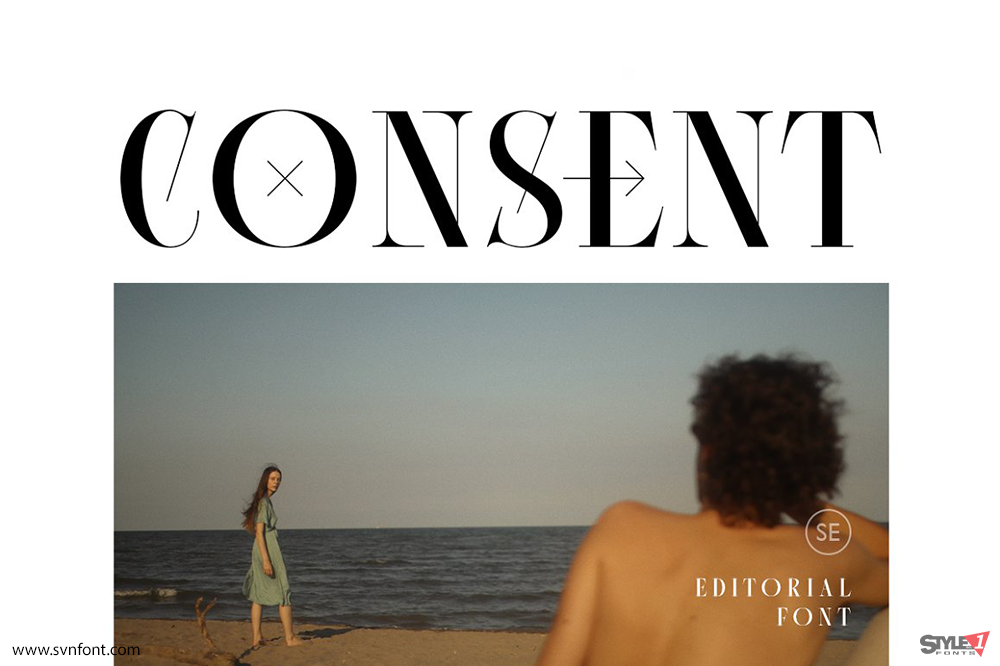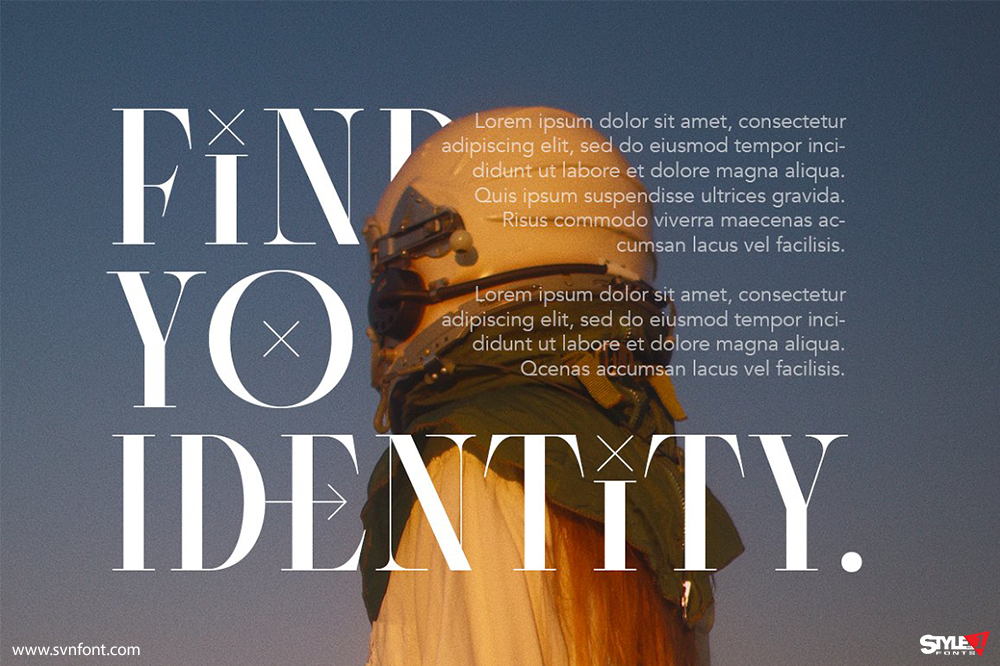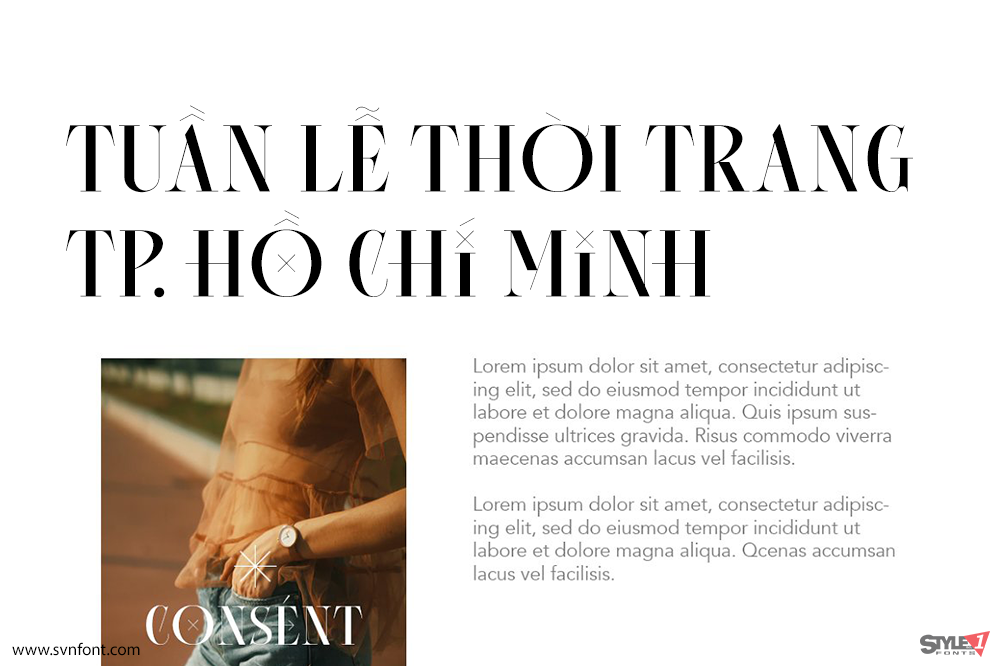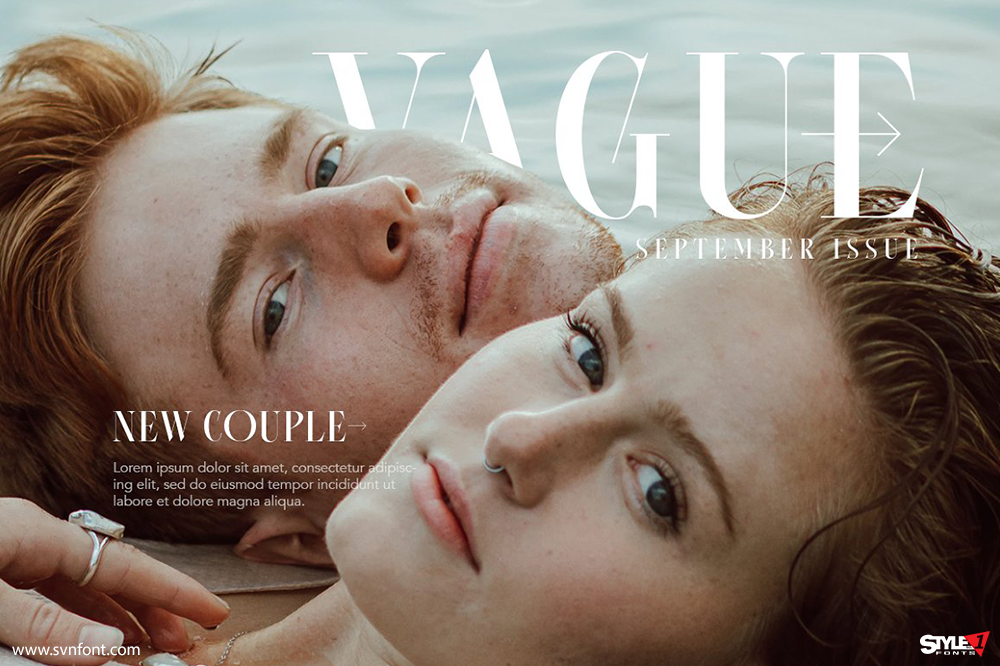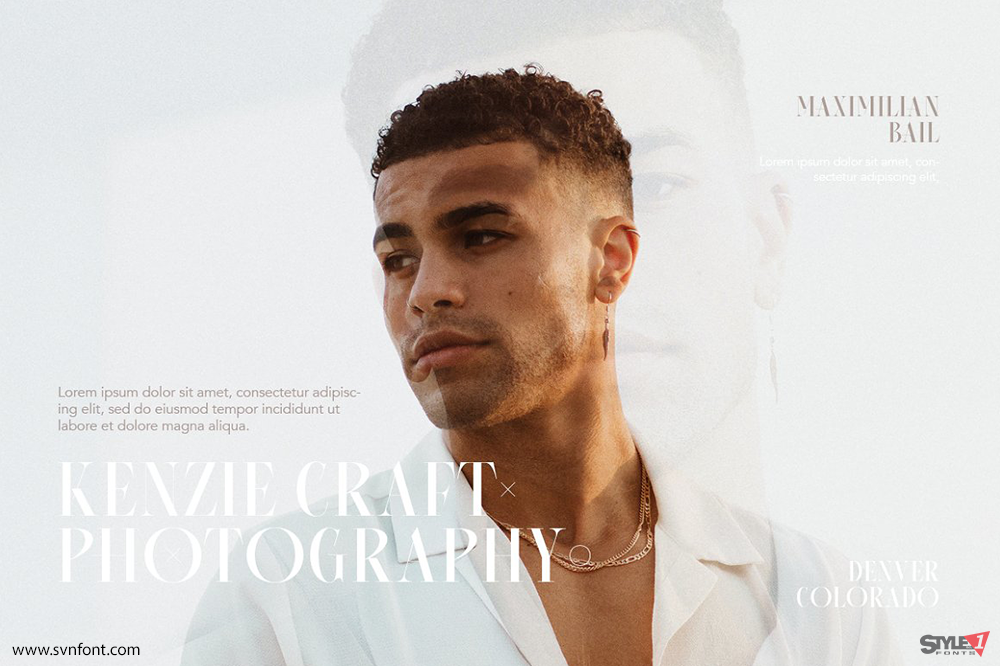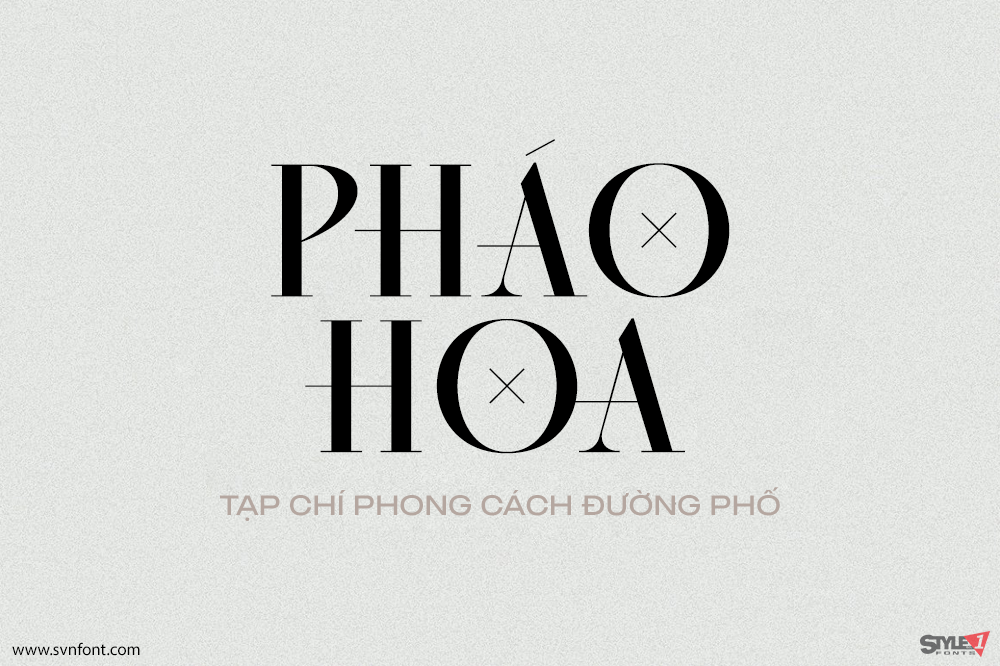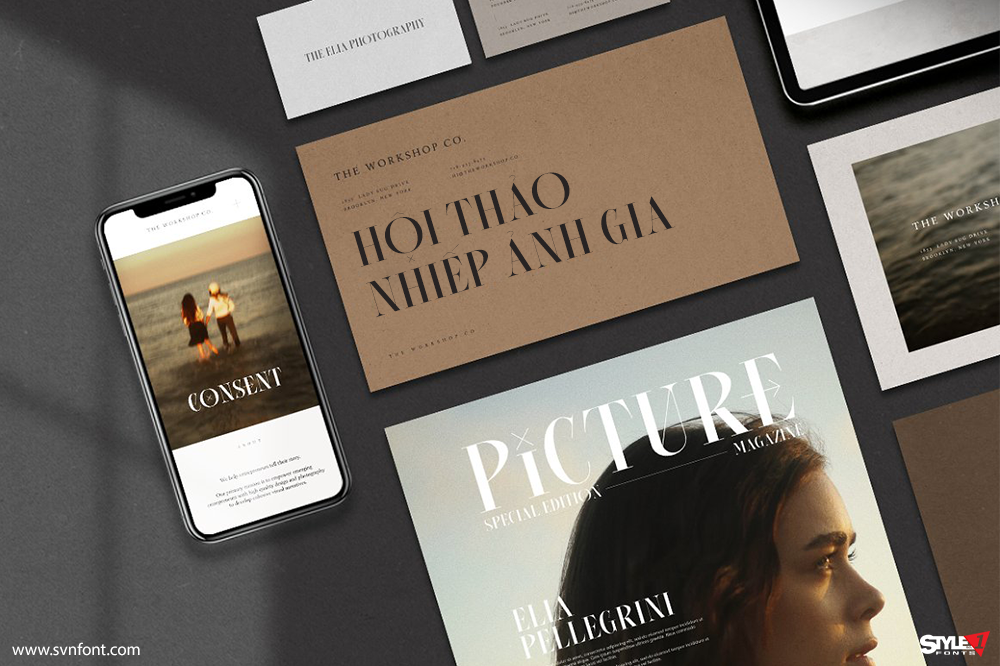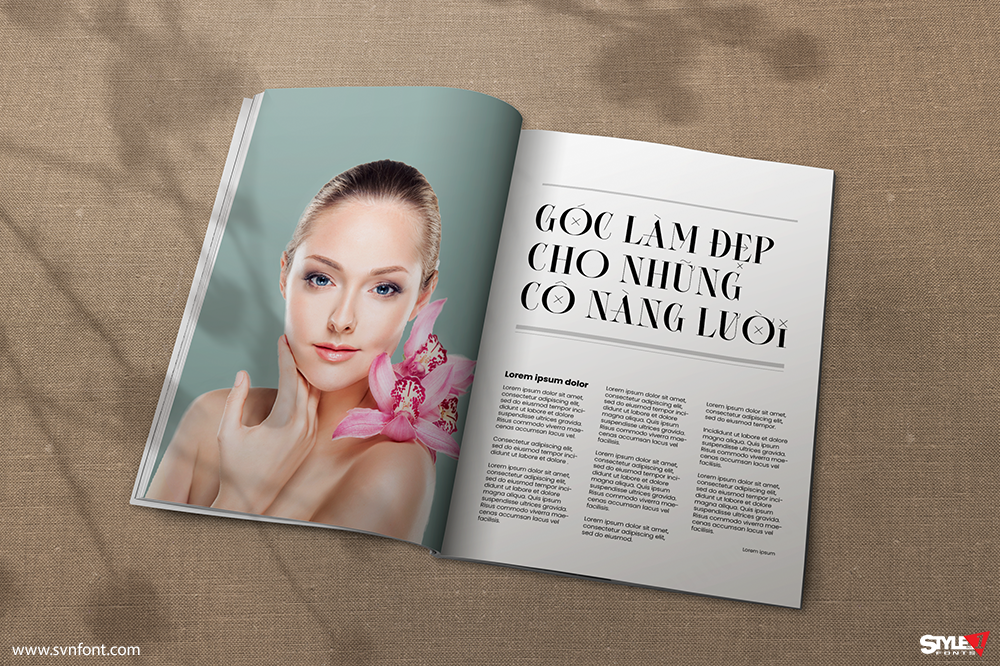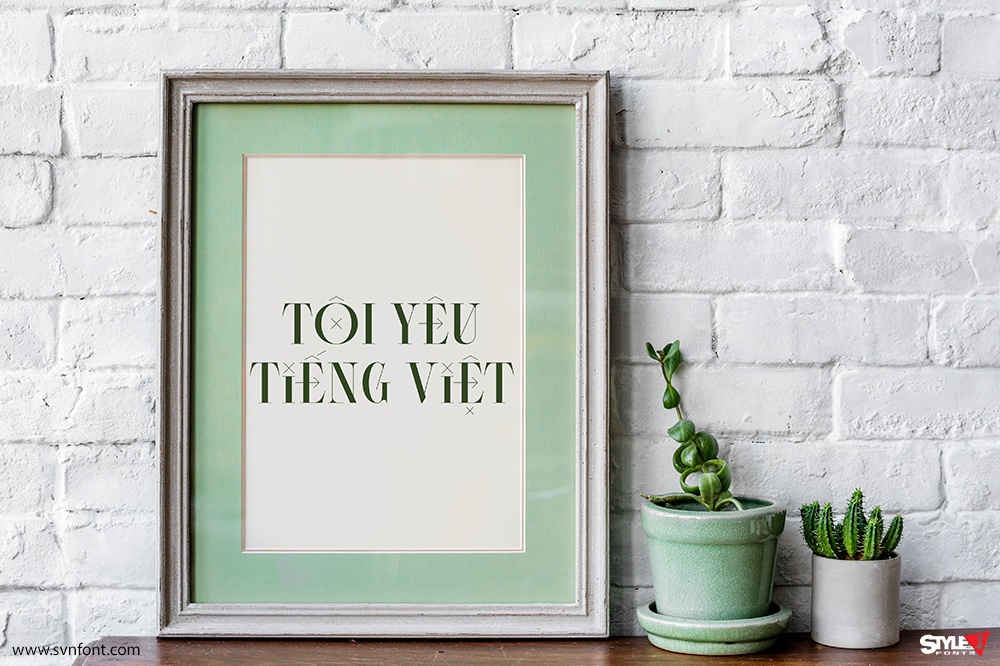
Consent là một font chữ serif mang phong cách biên tập với chữ thường độc đáo. Nhờ các tính năng đặc biệt, Consent sẽ giúp dự án của bạn trở nên nổi bật và thanh lịch hơn. Font chữ này phù hợp để sử dụng cho thương hiệu hoặc tiêu đề tạp chí. Bạn cũng có thể dùng font cho logo, branding và linh hoạt cho nhiều loại dự án khác! Không cần các bước phức tạp để sử dụng tính năng, chỉ cần gõ chữ thường, chữ hoa hoặc kết hợp cả hai.
Nhà thiết kế: Sarid Ezra
Nhà phát hành: Sarid Ezra